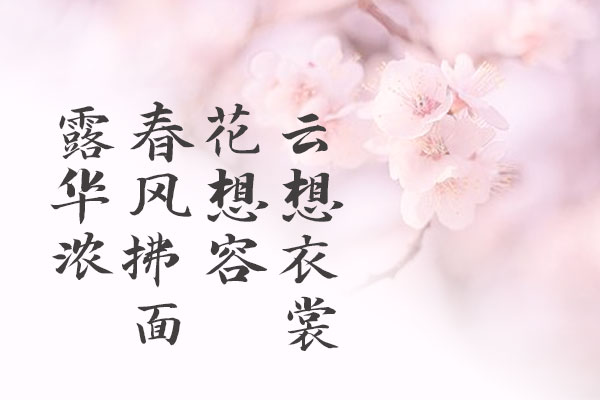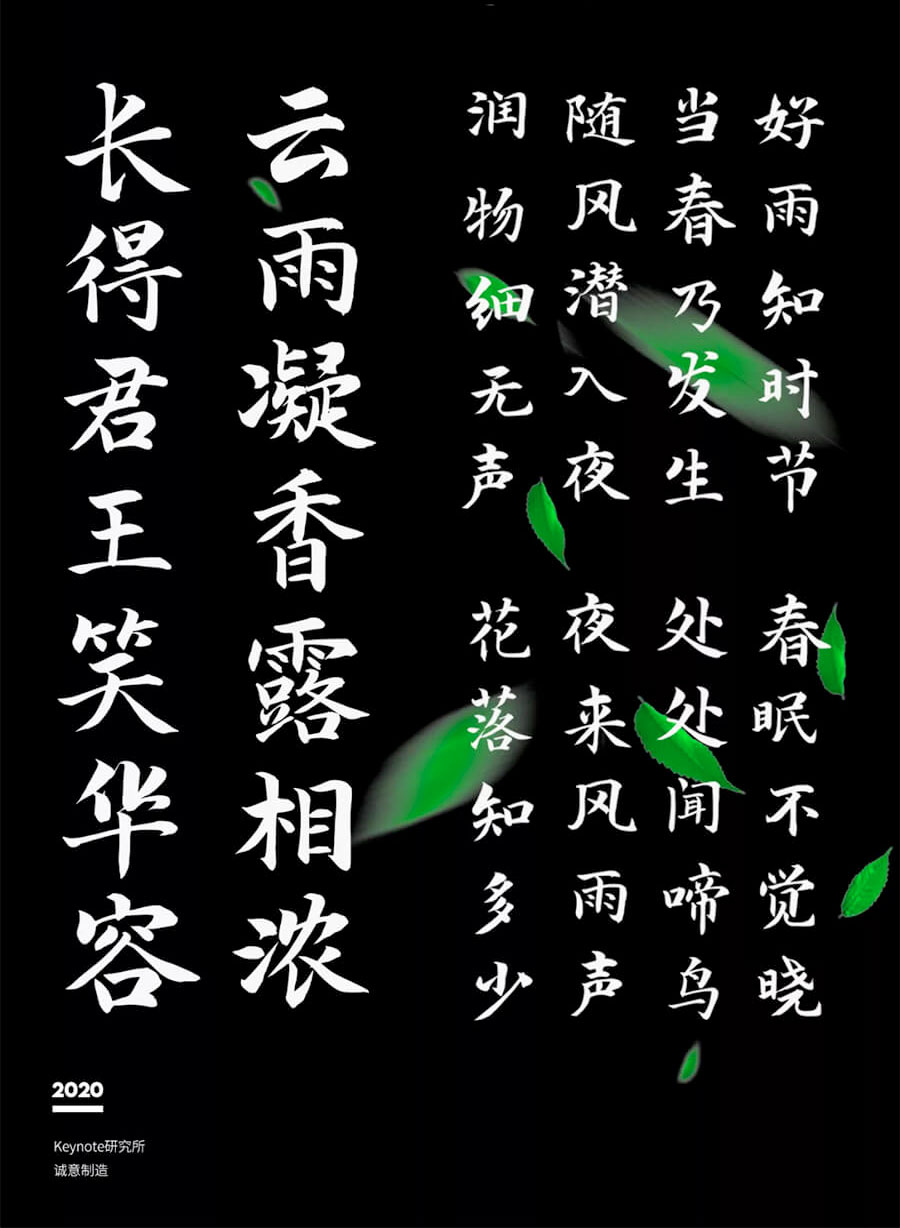
演示春风楷
演示春风楷是Keynote研究所的人生哥制作发布的一款毛笔字体,作者是徐占海。它包含标准的6763个字符,为简体中文楷书。
这款字体的设计注重解决用户问题,通过手写字稿转字体实现了灵活的应用。随着时间的发展,演示新手书与演示镇魂行楷两款字体应运而生,受到广泛关注和支持。今年3月,演示佛系体和演示悠然小楷两款免费可商用手写字体发布,而今天又迎来了三款免费可商用字体:演示春风楷、演示夏行楷、演示秋鸿楷。如果你对这款字体有任何疑问或建议,或者你想支持字体作者、加入字体创作等,可以关注作者的微信公众号:keynote研究所。
演示春风楷效果预览
演示春风楷字体效果预览